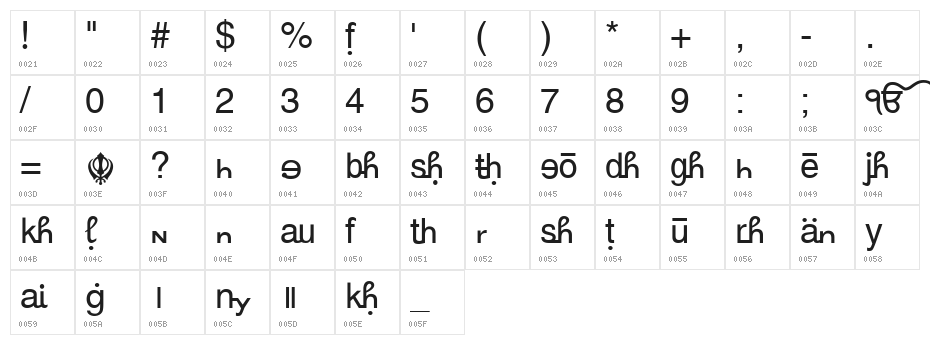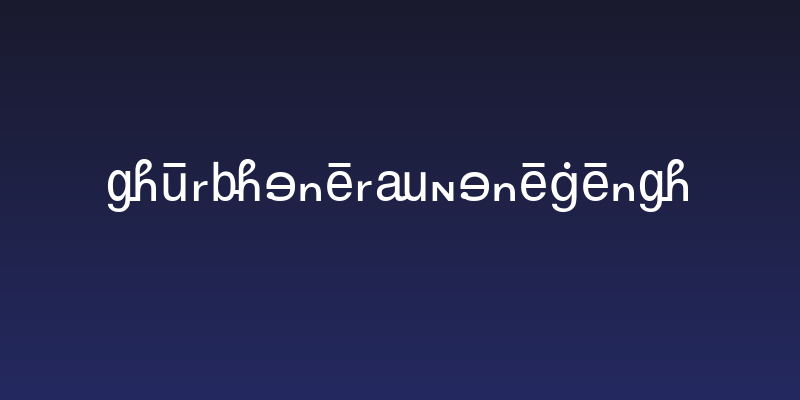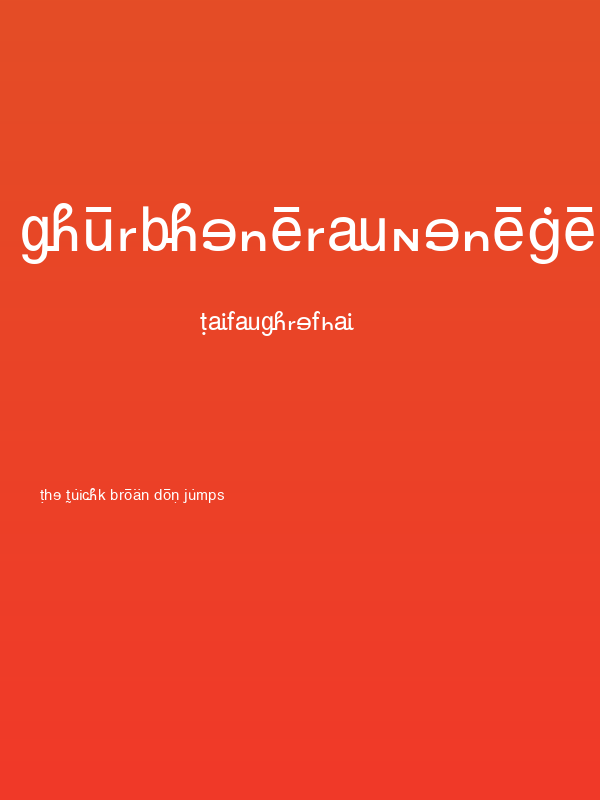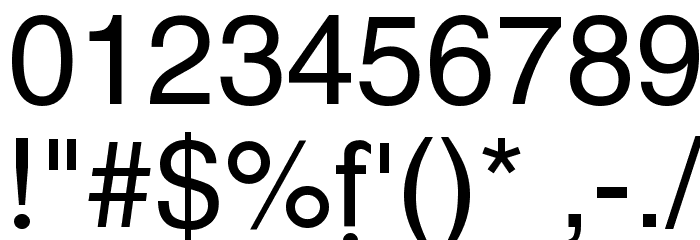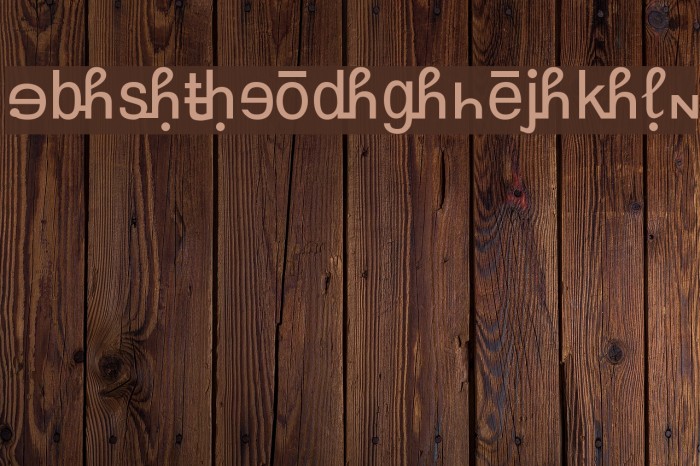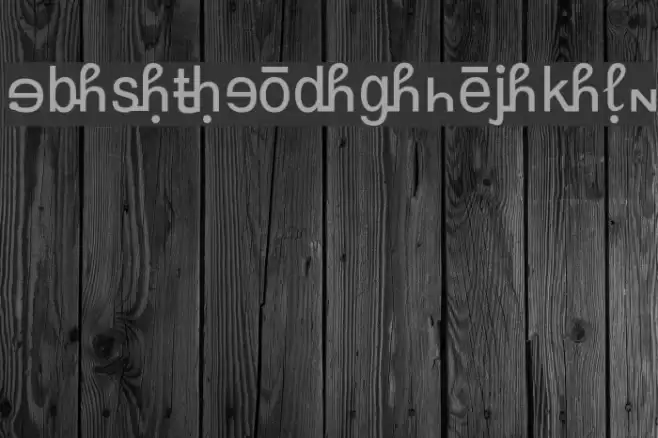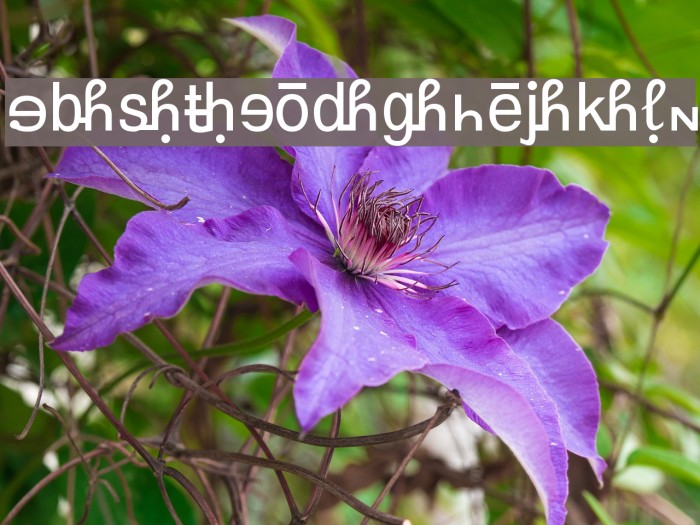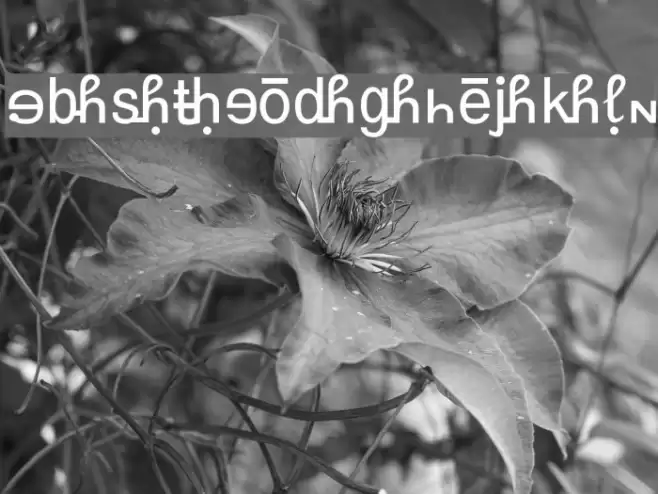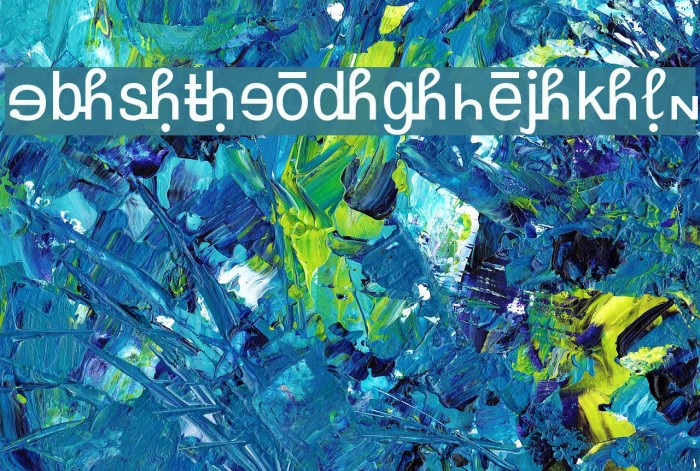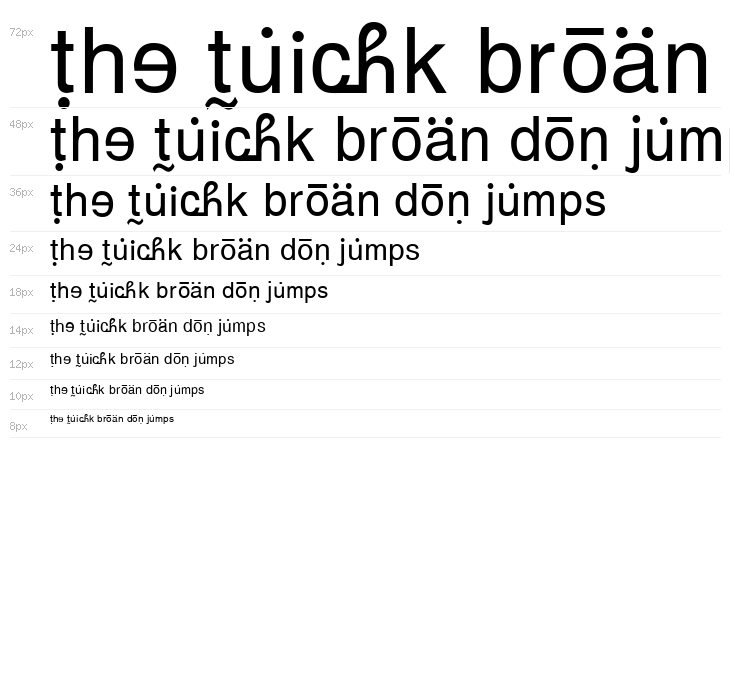
GurbaniRomanizing Font
| उपयोग का मामला | Body text, Educational materials, Linguistic projects |
| सुझाए गए प्रोजेक्ट | Ideal for linguistic projects, educational materials, and any application requiring clear text with diacritical marks. |